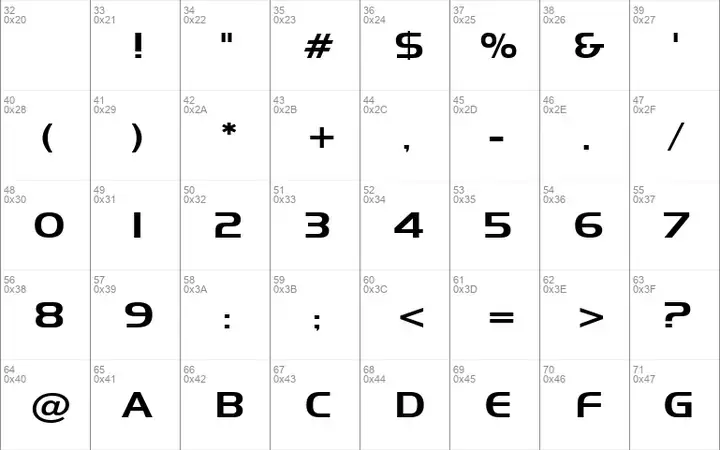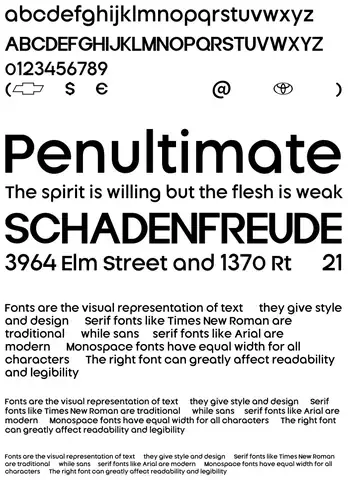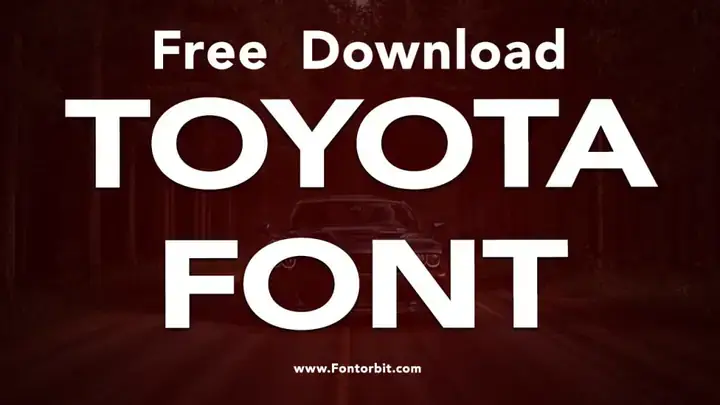
Font Chữ Toyota: Lịch Sử, Đặc Điểm Và Ứng Dụng Trong Thiết Kế Thương Hiệu
Giới thiệu chung
Trong thế giới thiết kế thương hiệu, việc lựa chọn một bộ font chữ phù hợp không chỉ là vấn đề thẩm mỹ mà còn ảnh hưởng trực tiếp đến nhận diện, giá trị và cảm xúc mà thương hiệu muốn truyền tải tới khách hàng. Đối với Toyota – một trong những tập đoàn ô tô lớn nhất và uy tín nhất trên hành tinh – font chữ không chỉ là một ký tự viết ra, mà còn là biểu tượng của sự tin cậy, đổi mới và cam kết chất lượng. Bài viết này sẽ đi sâu vào phân tích lịch sử, đặc điểm kỹ thuật, cách sử dụng và xu hướng phát triển của font chữ Toyota, đồng thời cung cấp một số gợi ý thực tiễn cho các nhà thiết kế và marketer muốn áp dụng font này trong các dự án của mình.
1. Lịch sử hình thành và phát triển của font chữ Toyota
1.1. Nguồn gốc ban đầu
Toyota được thành lập vào năm 1937 tại Nhật Bản và nhanh chóng trở thành biểu tượng của công nghiệp ô tô. Trước khi có một bộ font chính thức, công ty đã sử dụng các kiểu chữ truyền thống của Nhật Bản (Kanji, Hiragana, Katakana) kết hợp với tiếng Latin để thích nghi với thị trường quốc tế. Đến những năm 1970, khi Toyota mở rộng hoạt động ra toàn cầu, nhu cầu có một bộ nhận diện thống nhất, trong đó có font chữ, trở nên cấp bách.
1.2. Sự ra đời của “Toyota Type” (Toyota Font)
Vào năm 1995, Toyota hợp tác với công ty thiết kế đồ họa Nhật Bản Mitsubishi Design để tạo ra một bộ font riêng biệt, được gọi là “Toyota Type”. Bộ font này được thiết kế dựa trên các nguyên tắc:
• Đơn giản: Các nét chữ ngắn gọn, không rườm rà.
• Cân đối: Tỷ lệ chiều cao và chiều rộng hài hòa, tạo cảm giác ổn định.
• Đọc được: Dễ đọc ở mọi kích thước, từ biển hiệu lớn đến logo trên xe.
1.3. Các giai đoạn cải tiến
• 2005 – Toyota Bold: Để đáp ứng nhu cầu quảng cáo mạnh mẽ hơn, Toyota giới thiệu phiên bản “Bold” với độ dày nét chữ tăng lên, tạo cảm giác mạnh mẽ, năng động.
• 2015 – Toyota Light: Khi xu hướng thiết kế trở nên nhẹ nhàng và tinh tế, Toyota ra mắt “Light”, một phiên bản nhẹ hơn, thích hợp cho các tài liệu kỹ thuật và website.
• 2020 – Toyota Next: Đánh dấu bước chuyển mình sang kỷ nguyên số, “Toyota Next” được tối ưu hoá cho màn hình điện tử, hỗ trợ đa ngôn ngữ và có khả năng thích ứng tốt với các nền tảng UI/UX.
2. Đặc điểm kỹ thuật của font chữ Toyota
2.1. Kiểu chữ (Typeface) và các phiên bản
Phiên bảnĐộ dàyĐặc điểmỨng dụng chính
Toyota Regular400Độ dày trung bình, cân đốiVăn bản chính, tài liệu, website
Toyota Bold700Đậm, mạnh mẽTiêu đề, quảng cáo, biển hiệu
Toyota Light300Nhẹ, tinh tếNội dung phụ, chú thích, UI
Toyota Italic400 (nghiêng)Độ nghiêng 12°Trích dẫn, nhấn mạnh
Toyota Next400/600 (biến thể)Tối ưu hoá cho màn hìnhỨng dụng di động, dashboard xe
2.3. Hệ thống ký tự (Glyph Set)
Toyota Font bao gồm:
• Latin (A-Z, a-z, 0-9)
• Japanese Kanji, Hiragana, Katakana (hơn 5.000 glyph)
• Hangul (Korean)
• Cyrillic
• Greek
• Các ký tự đặc biệt (đánh dấu tiền tệ, ký hiệu thương hiệu, biểu tượng “Toyota”)
Điều này giúp Toyota duy trì sự đồng nhất trong mọi thị trường, dù là ở châu Á, châu Âu hay châu Mỹ.
2.4. Các tính năng đặc biệt
• Kerning tự động: Được tối ưu hoá để giảm khoảng cách không cần thiết giữa các ký tự, đặc biệt là các cặp “T” và “o”, “a” và “v”.
• Ligature: Sự kết hợp của các ký tự “fi”, “fl” để tạo ra một nét liền mạch, nâng cao tính thẩm mỹ.
• Hinting: Cải thiện độ sắc nét của chữ khi hiển thị trên các màn hình có độ phân giải thấp.
• OpenType Features: Hỗ trợ các tính năng như Small Caps, Oldstyle Figures, và alternate glyphs cho các trường hợp đặc biệt.
3. Ý nghĩa thương hiệu và cảm xúc truyền tải qua font chữ Toyota
3.1. Sự tin cậy và ổn định
Các nét chữ cân đối, không có góc cạnh quá nhọn, tạo cảm giác ổn định và đáng tin cậy. Điều này phản ánh triết lý “Toyota – luôn luôn đáng tin cậy” trong mọi sản phẩm và dịch vụ.
3.2. Đổi mới và công nghệ
Phiên bản “Toyota Next” với khả năng biến đổi trọng lượng và độ rộng cho phép các nhà thiết kế tùy chỉnh nhanh chóng, thể hiện tính linh hoạt và tiên phong trong công nghệ.
3.3. Độ thân thiện và gần gũi
Kiểu chữ không quá nghiêm túc, độ dày vừa phải, giúp người dùng cảm thấy gần gũi hơn, phù hợp với chiến lược “Làm cho cuộc sống dễ dàng hơn” mà Toyota luôn hướng tới.
4. Cách sử dụng font chữ Toyota trong thực tiễn
Nếu bạn đang lên kế hoạch cho một chiến dịch mới, một brochure, website hay thậm chí là giao diện dashboard xe, hãy cân nhắc sử dụng các phiên bản của Toyota Font – từ Regular, Bold, Light cho tới Toyota Next – để đảm bảo rằng thông điệp của bạn luôn truyền tải một cách rõ ràng, nhất quán và đầy sức mạnh.